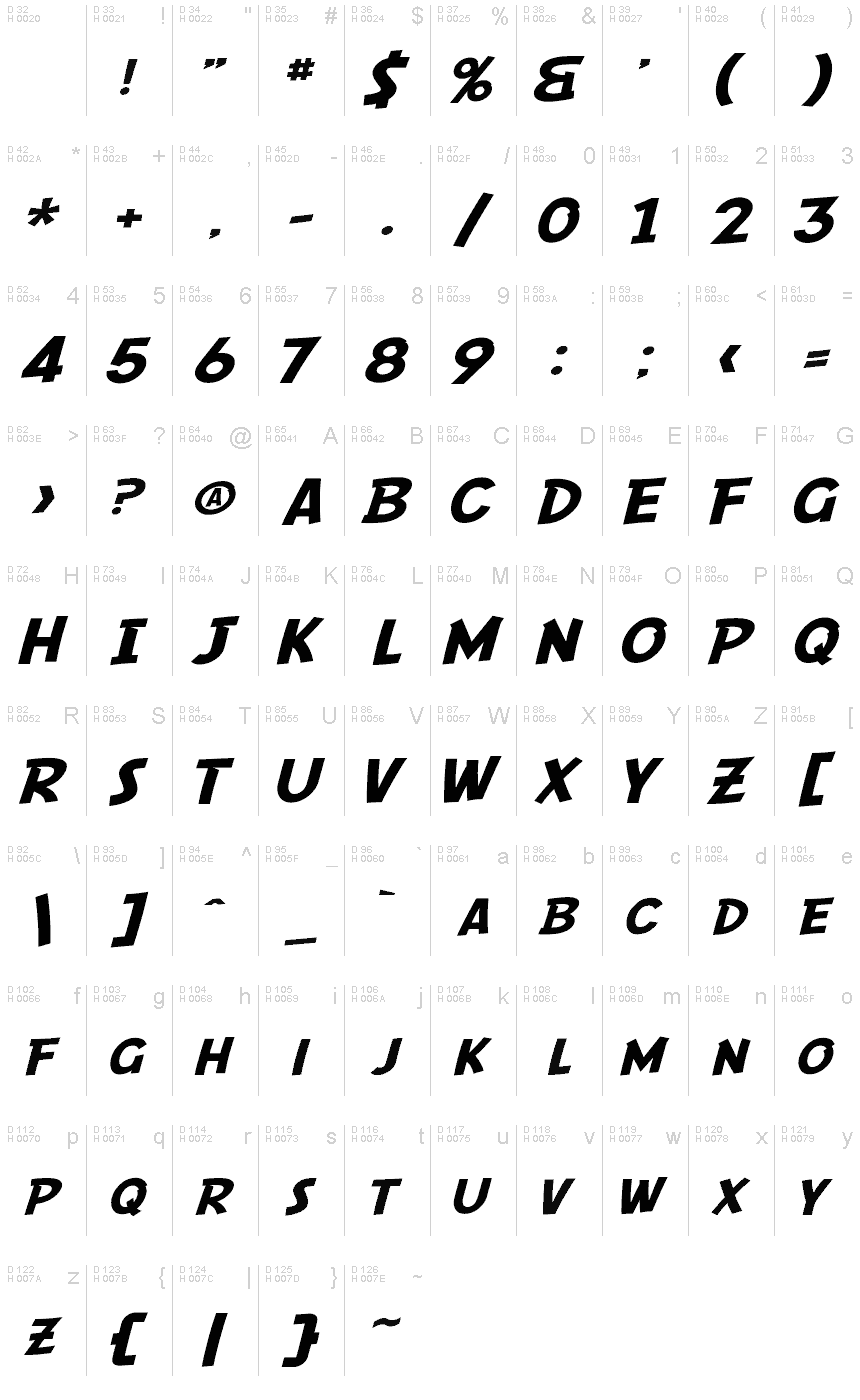
SF Comic Script Extended, z rodziny SF Comic Script, to dynamiczny i zabawny krój pisma, który wprowadza powiew fantazji i ekscytacji do każdego projektu. Ten stworzony przez ShyFonts Type Foundry font typu display wyróżnia się wyrazistą grubością i szerokim krojem, co nadaje mu znaczącej siły wyrazu.
Styl SF Comic Script Extended jest zdecydowanie komiksowy, pełen żartobliwych krzywizn i swobodnego charakteru, który naśladuje klasyczne komiksowe liternictwo. Przesadne kształty i przystępna natura czynią go doskonałym wyborem do angażujących tytułów, przyciągających wzrok logo czy dynamicznych animacji.
Rozszerzona szerokość tego fontu zwiększa jego widoczność na stronie czy ekranie, dzięki czemu idealnie nadaje się do nagłówków lub każdej kreatywnej pracy, w której zależy Ci, aby tekst był widoczny. Pogrubiona kreska dodaje dodatkowego nacisku, nie tracąc przy tym na czytelności.
Niezależnie od tego, czy używasz go w mediach cyfrowych, czy w druku, SF Comic Script Extended jest na tyle wszechstronny, że dodaje nutkę zabawy do projektów brandingowych, składów redakcyjnych, grafiki użytkowej, a nawet materiałów edukacyjnych, gdzie pożądany jest przyjazny ton. Dzięki unikalnemu połączeniu stylu i czytelności, ten font zachęca projektantów do nadania swoim kreacjom osobowości, przy jednoczesnym zachowaniu profesjonalnej jakości.